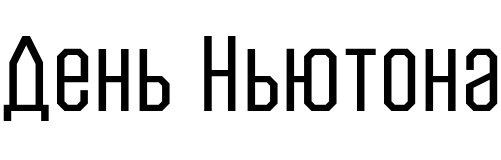
Асоціації зі шрифтом Fisionada RegularОсобистість і характер шрифта:
комп'ютерний, електронний, рівний, точний, логічний, холодний, автоматичний, техногенний, твердий, статичний, різкий, чіткий, стійкий, стабільний, прямокутний, міський, сучасний, машинний, інженерний, урбаністичний, креслярський, сталевий, індустріальний, залізний, мужній, промисловий, футуристичний, ламаний, кутастий, помітний, кінематографічний, ритмічний, гучний, високий, стрункий, гострий, худий, тісний, стиснений, ігровий, надійний, впевнений, переконливий, серйозний, сильний, військовий, армійський, байдужий, гранчастий, рубаний
комп'ютер, конструктор, креслення, інженер, автоматика, урбаністика, електроніка, авто, інструмент, робот, гра, техніка, прилад, автомат, технології, залізо, фантастика, кіно, лего, іграшка, кубики, хмарочос, кінотеатр, архітектура, комп'ютерна гра, дизайн, Місто, гаджет, промисловість, війна, армія, зброя, завод, металургія, верстат, тара, склад, порт, ящик, патрони, ремонт, депо, шолом, уніформа, вагон, шутер, екшен, страйкбол, взуття, айтішник, IT, айті, астрономія Шрифт має ознаки стилів: